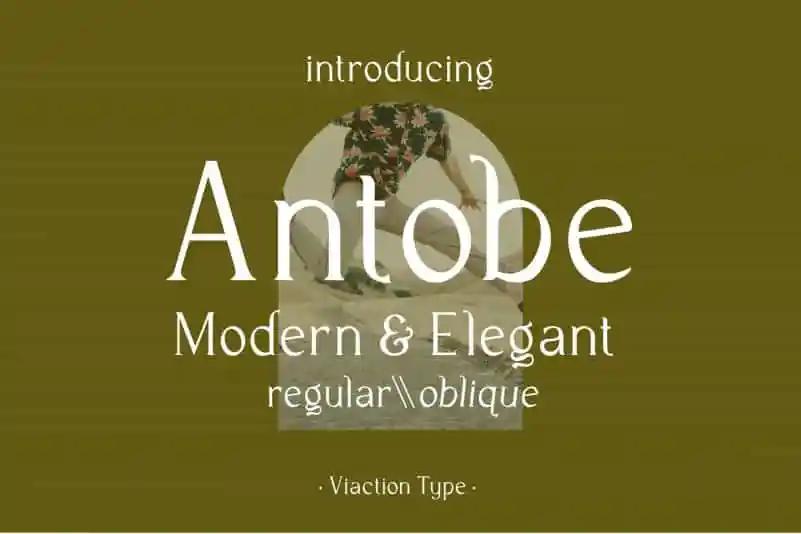
A Antobe Serif Font é uma escolha perfeita para quem busca um equilíbrio entre estética e praticidade no design. Ideal tanto para ambientes modernos quanto elegantes, esta fonte serif oferece linhas finas que se adaptam perfeitamente a layouts contemporâneos, proporcionando uma textura sofisticada sem perder sua funcionalidade em projetos de design variados. Confortável tanto para uso regular quanto oblique, possui dois estilos distintos. Além disso, seu design inclui ferramentas multilinguísticas que permitem uma utilização mais fácil e versátil para diversos propósitos de design. Seja você um designer gráfico ou um amante da arte, a Antobe Serif Font traz uma linguagem clara e elegante às suas criações, adaptável à sua necessidade. Experimente essa fonte moderna e sofisticada para adicionar profundidade ao seu trabalho.